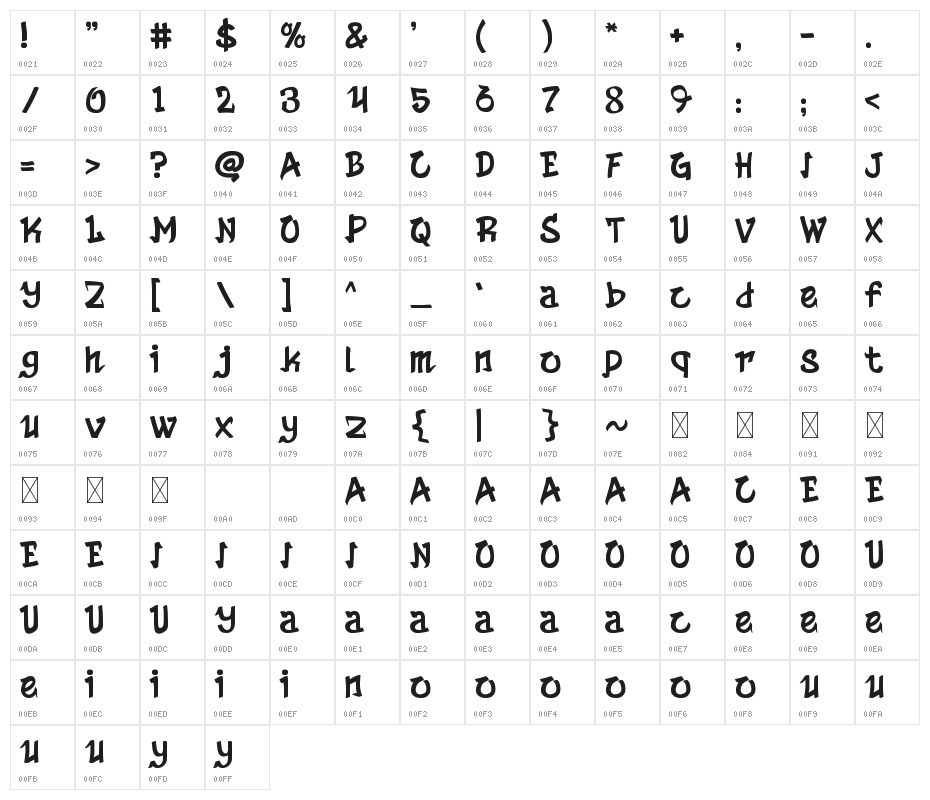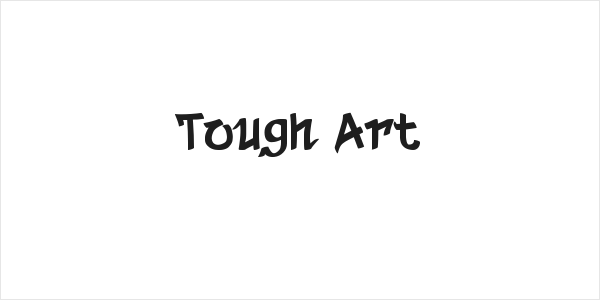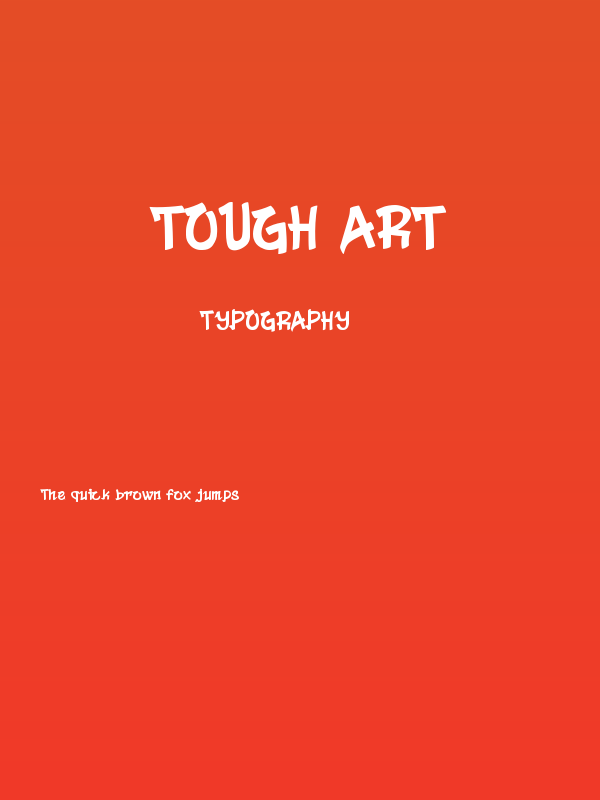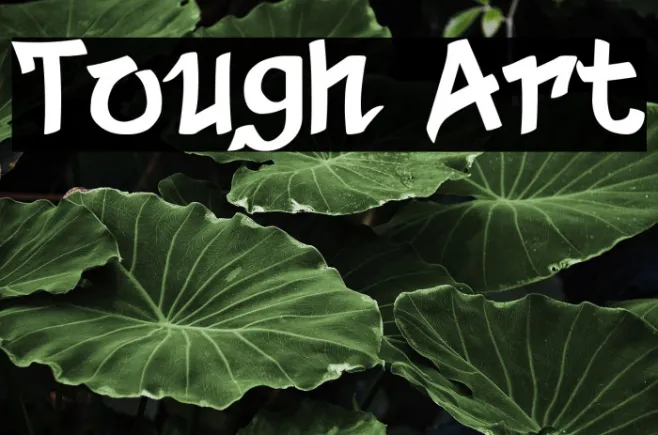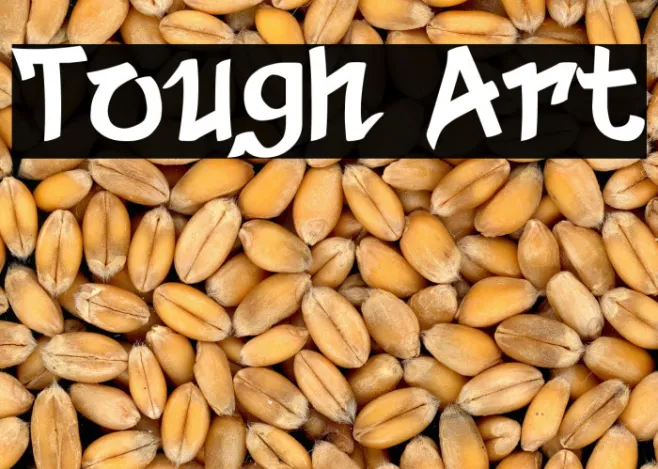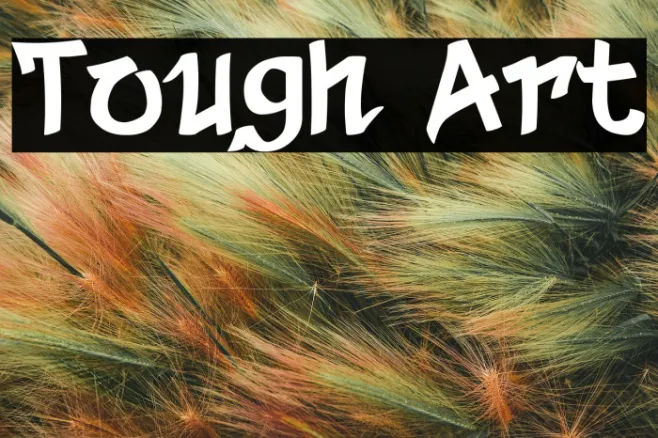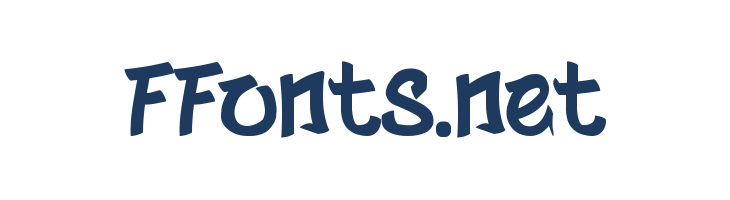
Tough Art Font
✎ Graffiti
| Vorgeschlagene Projekte | Ideal for street art-inspired designs, posters, album covers, and creative branding projects. |